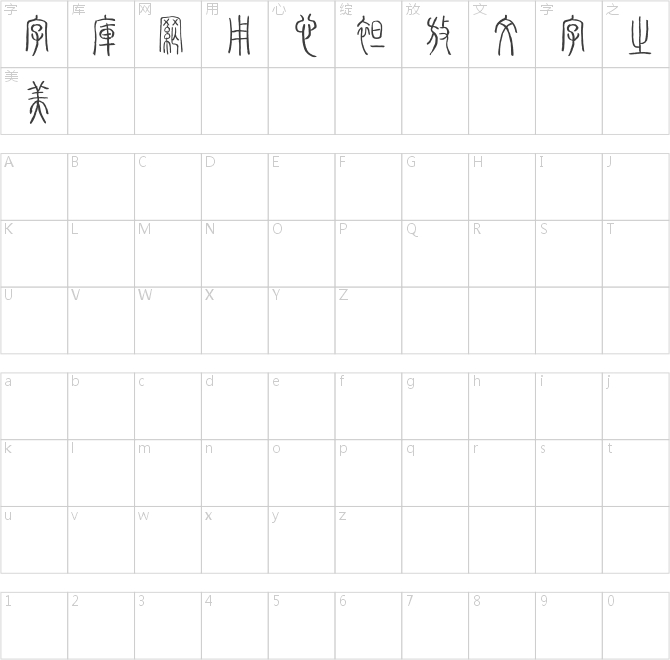
字体名称: 李亲湖篆体字库
李亲湖篆体字库介绍
李亲湖篆体字库的字长方偏瘦形,每一字端正,中锋用笔,笔画横平竖直,圆劲均匀,粗细一致,画与画、竖与竖之问等距平行,随意起随意收,方中寓圆结字左右对称,上下对称,圆弧形笔画左右倾斜度的对称,上紧下松,美态多姿,仔细品尝味道浓浓。视觉效果强烈地冲击着眼球,让品尝者神游其间、沉醉于中。